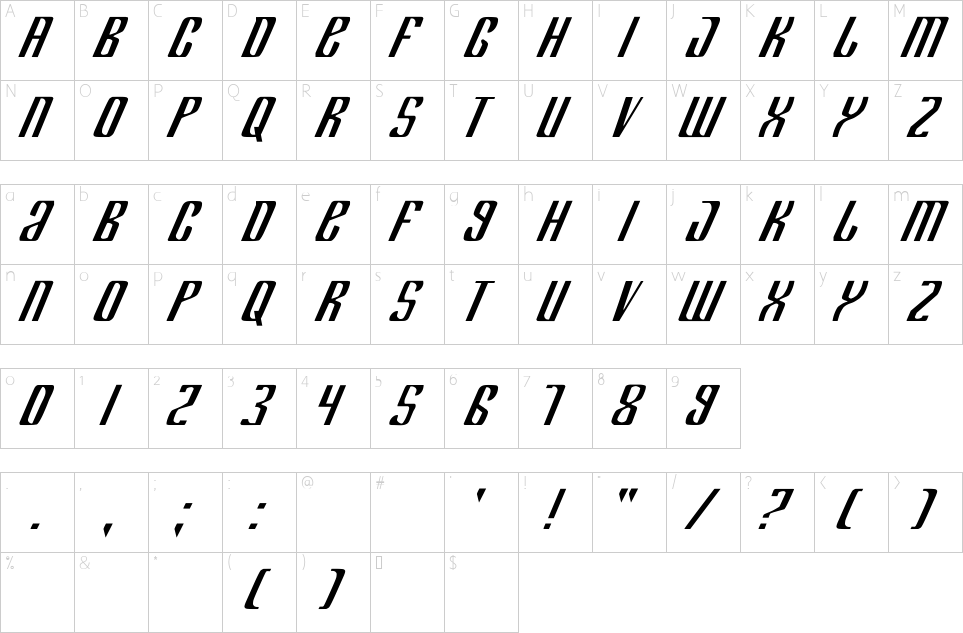
Aqui está uma descrição em português, envolvente e natural, para a página de download da fonte ‘Department K Font | 1001 Free Fonts’: Através de seu design aprimorado, a fonte ‘Department K’ oferece uma alternativa elegante e moderna para as fontes mais convencionais. Inspirada em Iconian Fonts, esta fonte é ideal para quem busca uma aparência sóbria e sofisticada. O design minimalista de ‘Department K’ garante uma legibilidade perfeita em todos os dispositivos, proporcionando um texto limpo e profissional. Ideal tanto para ambientes corporativos quanto para publicações pessoais, esta fonte é uma escolha inteligente para quem valoriza a elegância no design. Sua disponibilidade gratuita e ampla gama de utilização torna ‘Department K’ uma fonte indispensável para qualquer designer que busca recursos de design úteis e de qualidade. Instale-a em seu próximo projeto e deixe sua marca com uma elegância inconfundível.